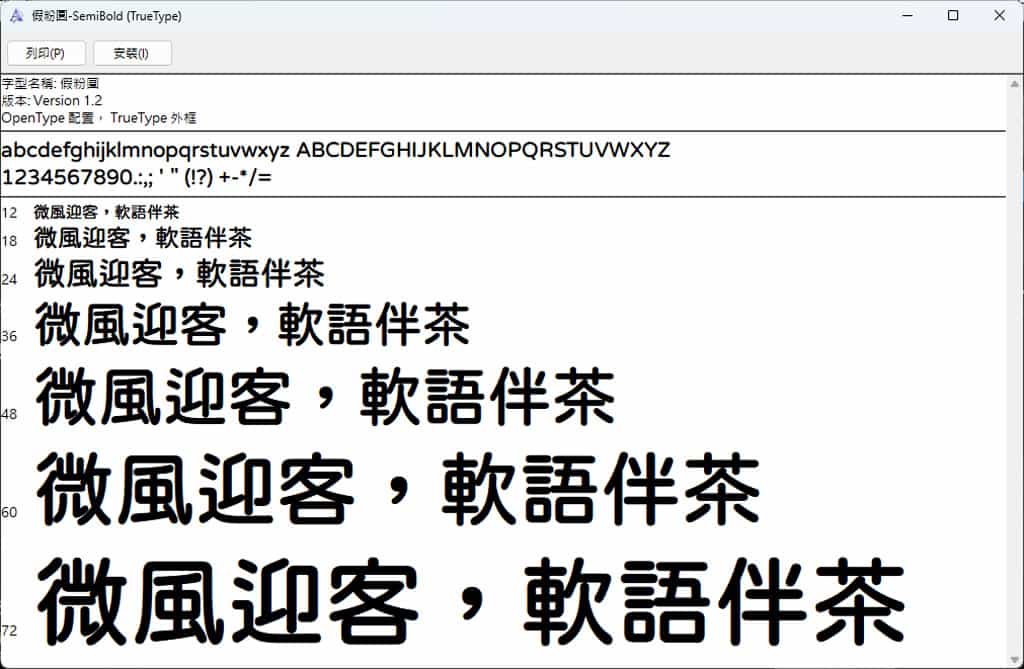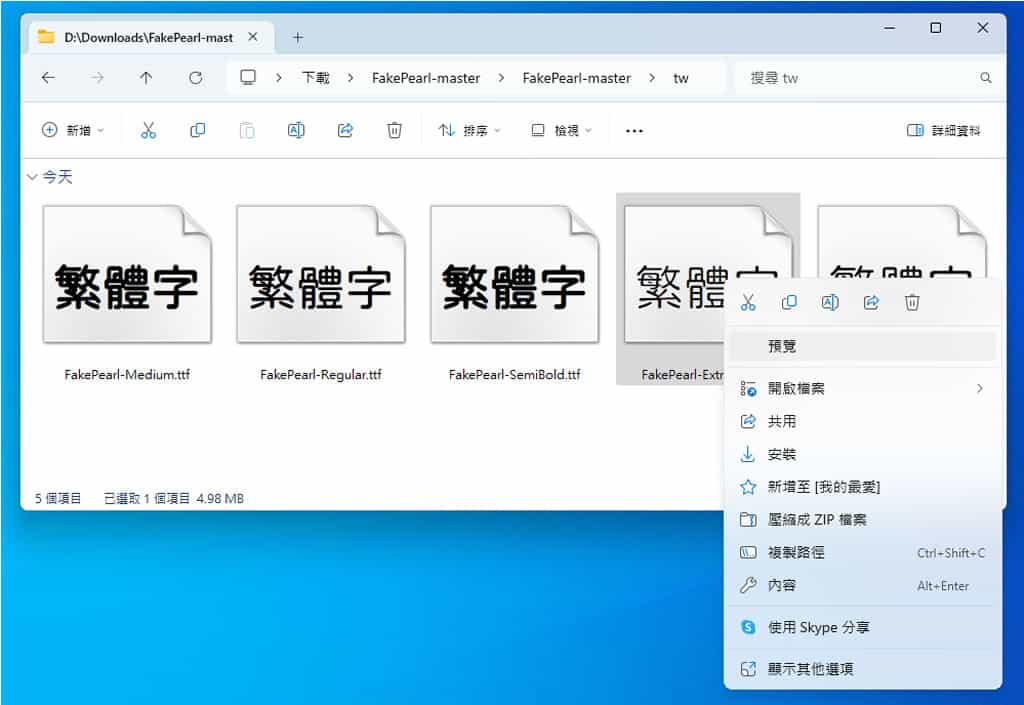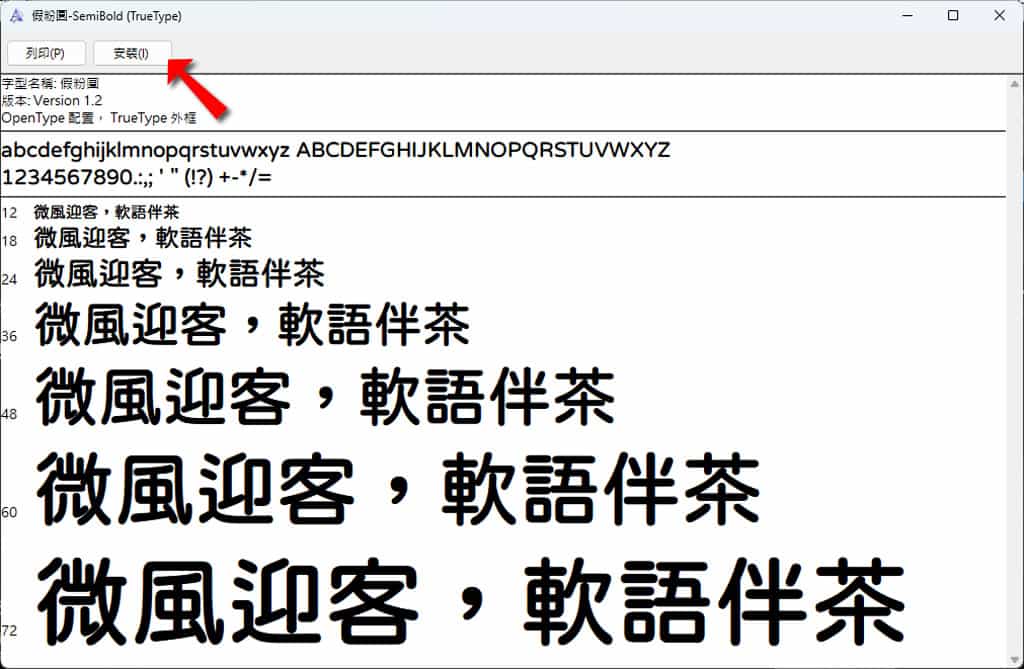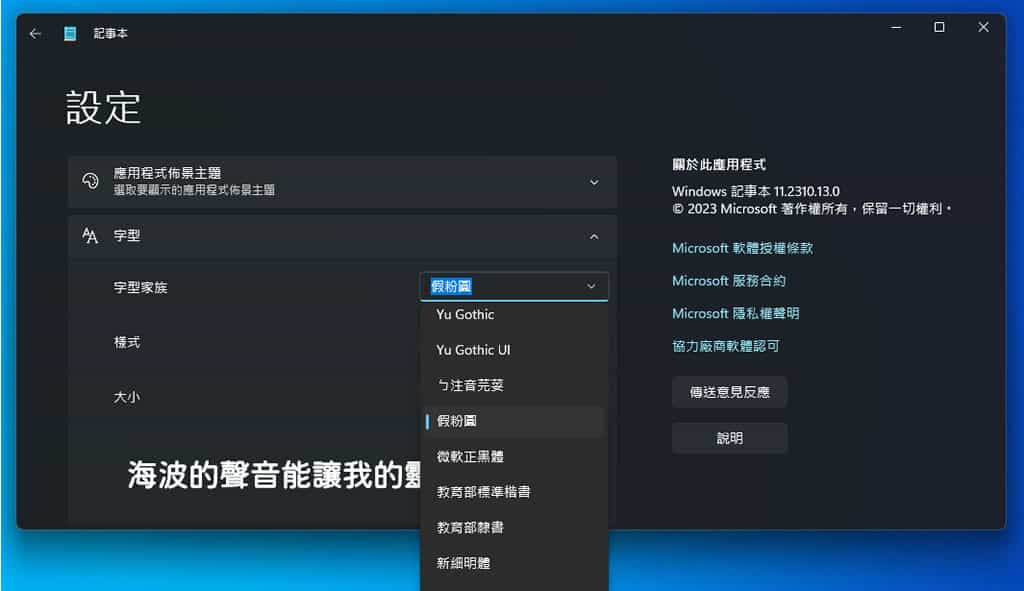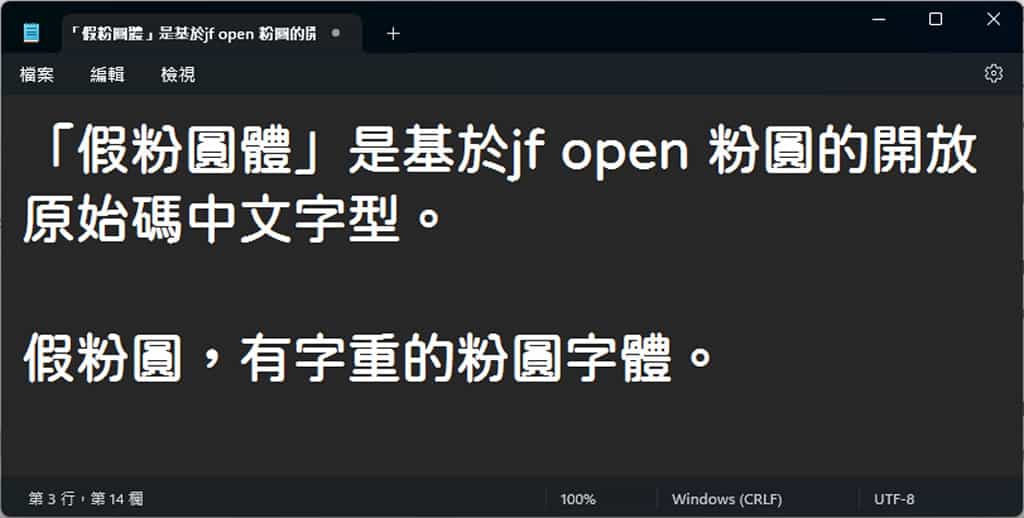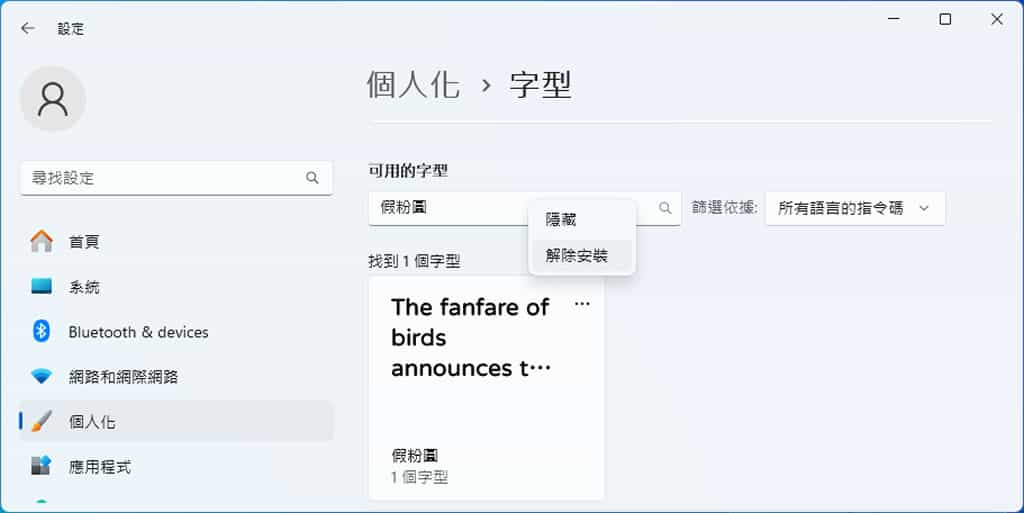
首頁免費字型中文字型 FakePearl 假粉圓體:源於 JF Open 粉圓字型,5 種字重免費可商用 「FakePearl 假粉圓體」是一個源於「jf open 粉圓字型」的開放原始碼中文字型,與原版不同,假粉圓體擁有五種不同的字重。原本的粉圓字體以 Regular 字重呈現,另外透過程式自動產生 ExtraLight、Light、Medium、SemiBold 新的字重。根據作者自述,由於「假粉圓體」是由程式自動產生字重,有些字的方向可能會錯亂,若遇到問題建議回報有問題的字。此外,這個字體採 SIL Open Font License 1.1 協議授權,因此所有人都能免費下載使用,也能用在商業用途上。 🔔 不錯過任何精彩! 立即訂閱我們的 LINE 官方帳號 每次發佈新文章時,您將會第一時間收到本站文章連結通知,輕鬆掌握最新資訊! 使用 LINE 追蹤文章更新 §相關文章,還可以參閱:字言字型免費中文字體1—手繪體:融合宋楷雙韻的手繪塗鴉字型,免費可商用結合傳統與現代美學的台灣日曆字型「日曆體」免費開源下載荊南麥圓體 KN Maiyuan:可愛圓潤的免費商用中文字體LINE Seed TW:圓潤親切的繁體中文字體,不但免費還可商用香萃刻宋:免費可商用的仿古雕刻宋體字型,展現濃厚人文與視覺張力 中文繁體字型,包含五種字重,適合個人與商業用途 1.進入「FakePearl 假粉圓體」GitHub 官網,點選頁面右上綠色「Code」按鈕,再點選「Download ZIP」。 2.解壓縮下載的檔案並依序開啟「FakePearl-master > tw」資料夾,就可以看到 ExtraLight、Light、Regular、Medium及 SemiBold 5 種不同字重的 ttf 字型檔案,滑鼠右鍵點擊,可選擇預覽或安裝該字型。 下圖是預覽,也可以在此處安裝字型。 3.完成安裝後,在應用軟體的字型處選擇「假粉圓」即可運用,下圖是 Windows 內建「記事本」應用軟體字型設定視窗。 下圖是實際運用。 4.想要移除安裝的字型,可以在「設定 > 個人化 > 字型」處,找到「假粉圓」再移除。 FakePearl 假粉圓體官方網站:https://github.com/max32002/FakePearl